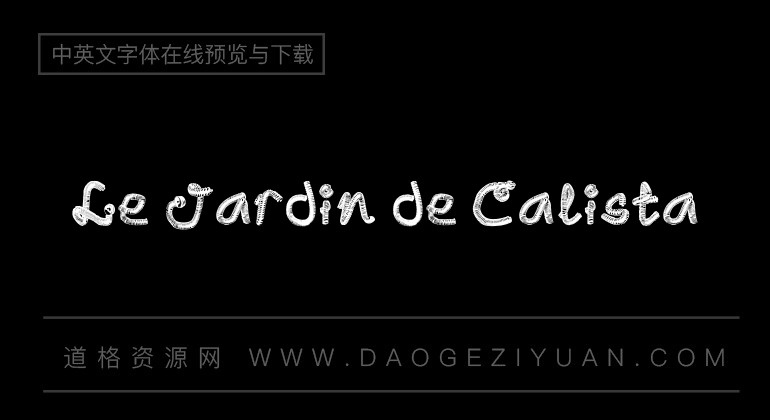
Le Jardin de Calista
Le Jardin de Calista 是一种漂亮的手写风格字体,由艺术家 Sabrina Lopez 创作。这种字体具有流畅的笔触和轻盈的线条,适用于许多不同的设计项目,特别是那些需要一种柔和、优雅的字体。 这种字体具有多种不同的变体和替代字形,使得它非常适合用于标志、包装设计、卡片、海报等各种创意设计项目。它的风格也适合用于婚礼和其他特殊场合的设计项目。 总的来说,Le Jardin de Calista 是一种非常优美、优雅的字体,值得在你的设计项目中使用。
Le Jardin de Calista是一款非常不错的手写艺术字体,具有很好的视觉感,适合于文化类的宣传设计、商业类品牌的广告和产品包装设计以及个性化文字排版等较多场景。
Le Jardin de Calista字符映射图